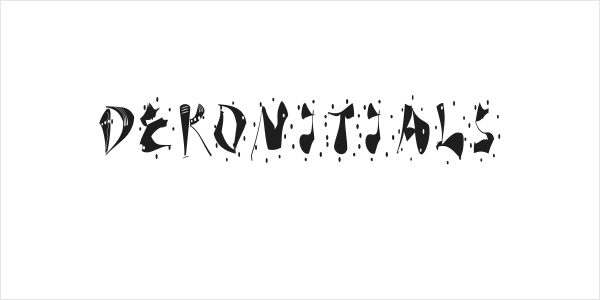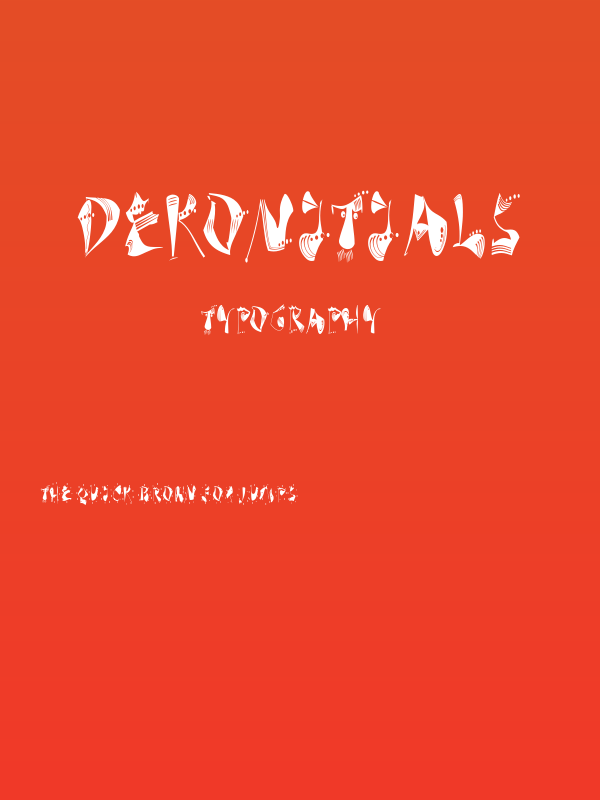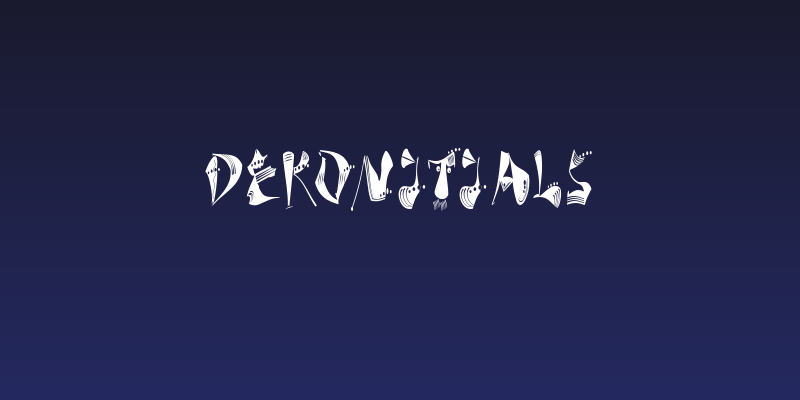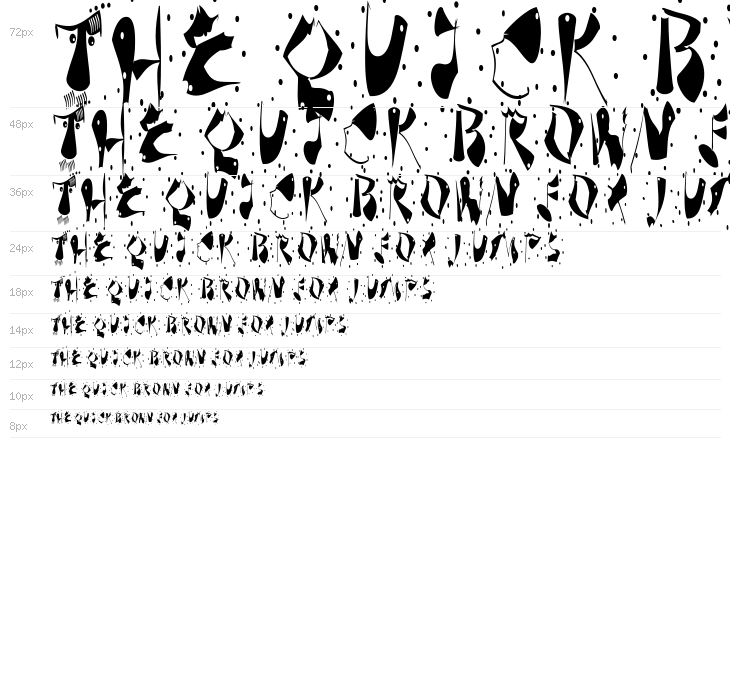
DeKonitials Font
| Stile generale | Avant-garde, Artistic |
| Caso d'uso | Logos, Posters, Album covers |
| Progetti proposti | Ideal for artistic posters, album covers, creative branding, and any project that requires a bold, artistic statement. |